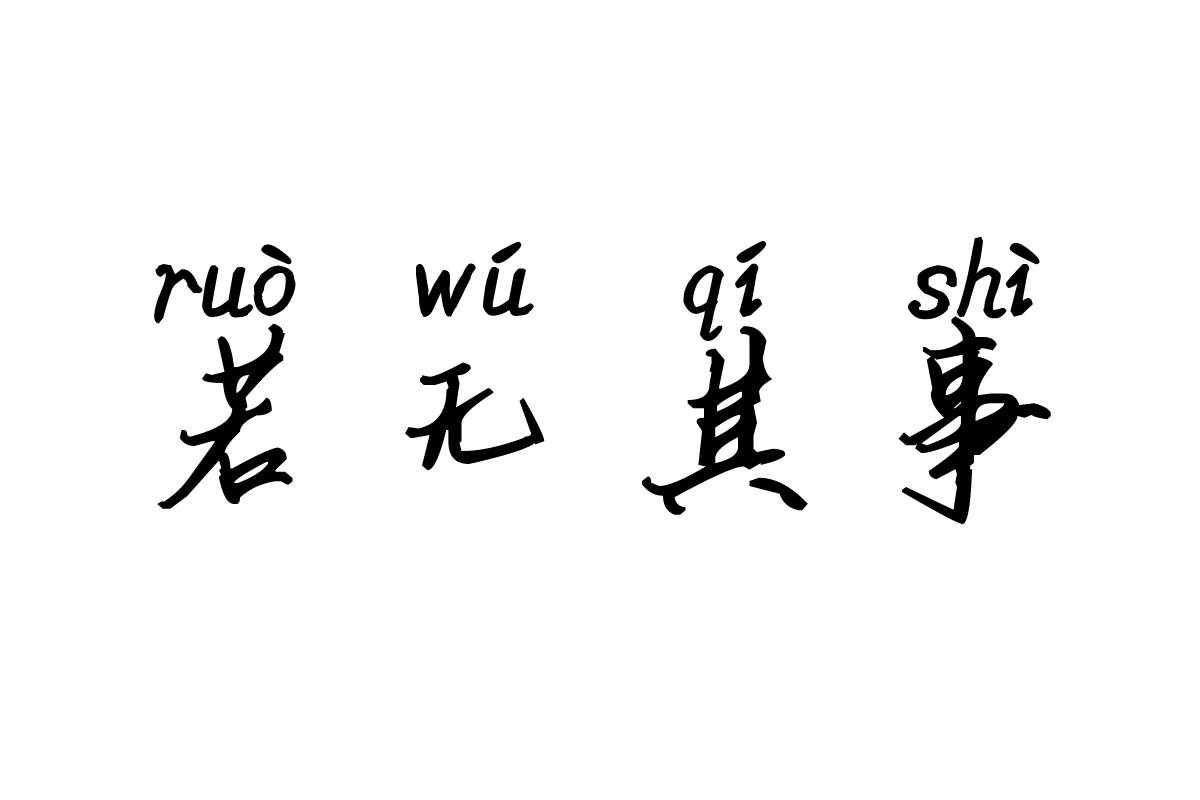
米开咖啡别加糖拼音体是一种中文字体,它的设计灵感来源于咖啡杯上的图案和文字。这种字体的特点是简洁、现代,适合用于各种商业和广告宣传材料。
字体特点:
1. 字形简洁明了,易于阅读。
2. 线条流畅,没有过多的装饰性元素。
3. 颜色搭配协调,给人一种清新的感觉。
4. 适合用于各种类型的文本,如标题、正文、副标题等。
适用场景:
1. 商业广告:用于制作宣传册、海报、横幅等。
2. 网站设计:用于制作网页标题、正文、按钮等。
3. 印刷品:用于制作报纸、杂志、书籍等。
4. 包装设计:用于制作产品包装、标签等。